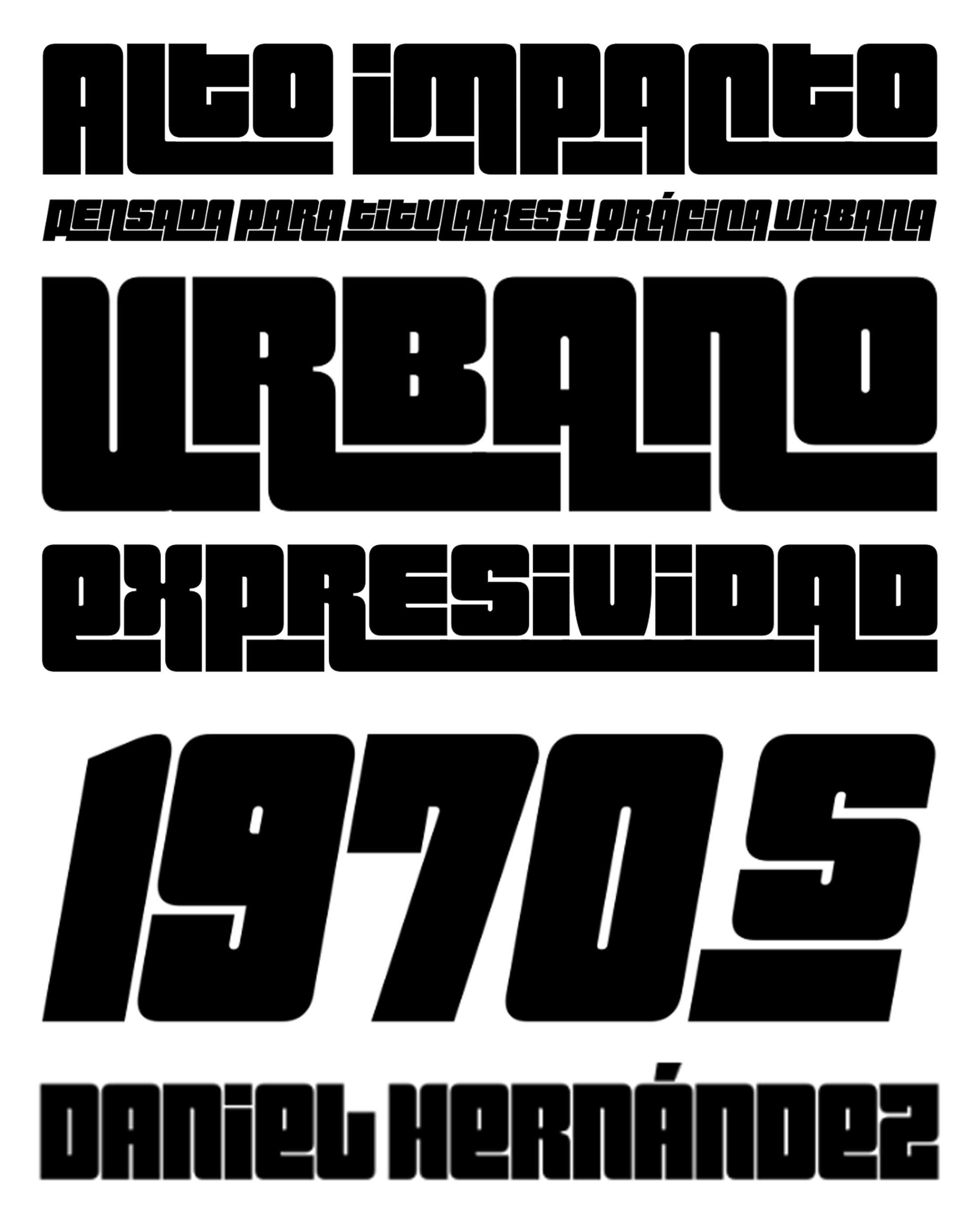
| Descripción | Pincoya Black Pro es un tipo de letra basado en un cartel de la Guerra Civil española, complementado con gráficos desarrollados en "La Unidad Popular" (coalición política chilena) durante los años setenta. Pincoya tiene muchos caracteres alternativos en formato Opentype que proporcionan múltiples opciones a la hora de componer un texto. Es una fuente ideal para frases de gran impacto, logotipos, maquetación de revistas, diseño de carteles, etc. Entre los idiomas se incluyen: Latín básico, europeo occidental, euro, catalán, báltico, turco, centroeuropeo, rumano y latín panafricano. |